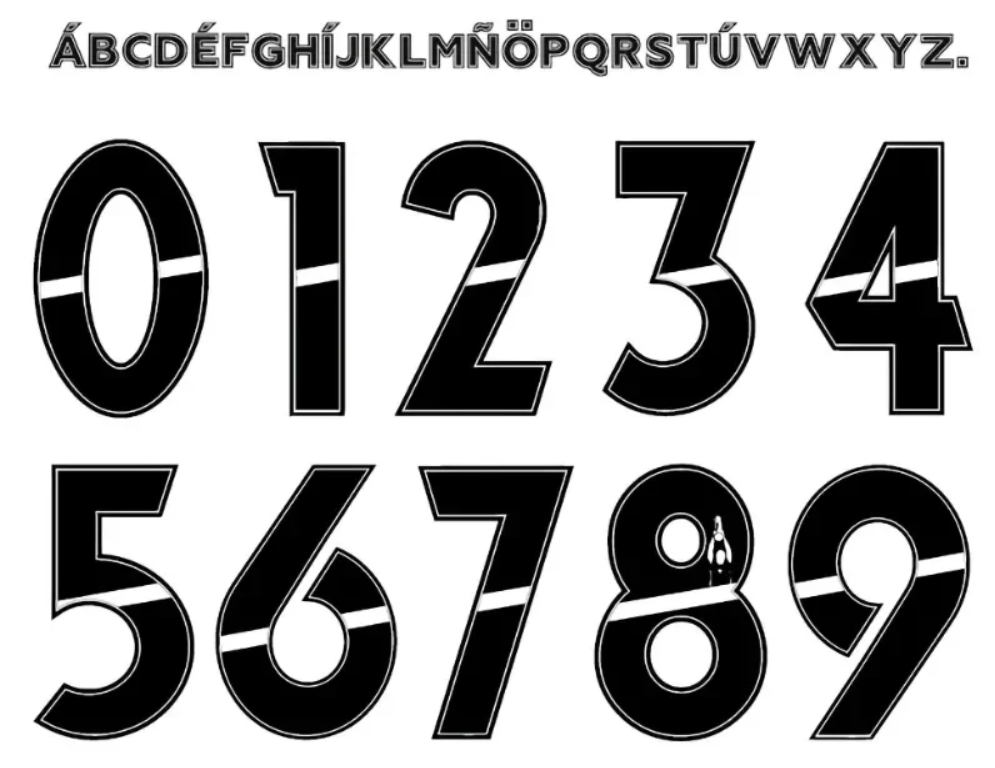
Se você é designer esportivo, estampador ou apenas um torcedor fanático querendo personalizar o manto alvinegro, chegou ao lugar certo. Disponibilizamos para download a Fonte Corinthians 2025, a tipografia oficial utilizada nos uniformes desta temporada.
Esta fonte foi desenvolvida para acompanhar a nova coleção lançada pela Nike, parceira histórica do Timão. A tipografia não serve apenas para identificar os jogadores em campo; ela carrega a identidade visual de um dos maiores clubes do Brasil, complementando o design das camisas I (Branca) e II (Listrada) com um toque de modernidade e agressividade.
Estilo Visual e Identidade
A tipografia de 2025 segue uma linha minimalista, mas impactante. Diferente de anos anteriores onde a Nike optou por fontes mais arredondadas ou com serifas clássicas, a versão 2025 aposta em cortes retos e ângulos agudos internos.
• Design: Geométrico e “blocky” (blocado), garantindo excelente legibilidade à distância e na transmissão televisiva.
• Aplicação: Utilizada para os nomes dos jogadores e a numeração nas costas, além da numeração menor no calção.
• Detalhes: A base dos números possui uma leve inclinação, sugerindo movimento e velocidade, características essenciais para o futebol moderno.